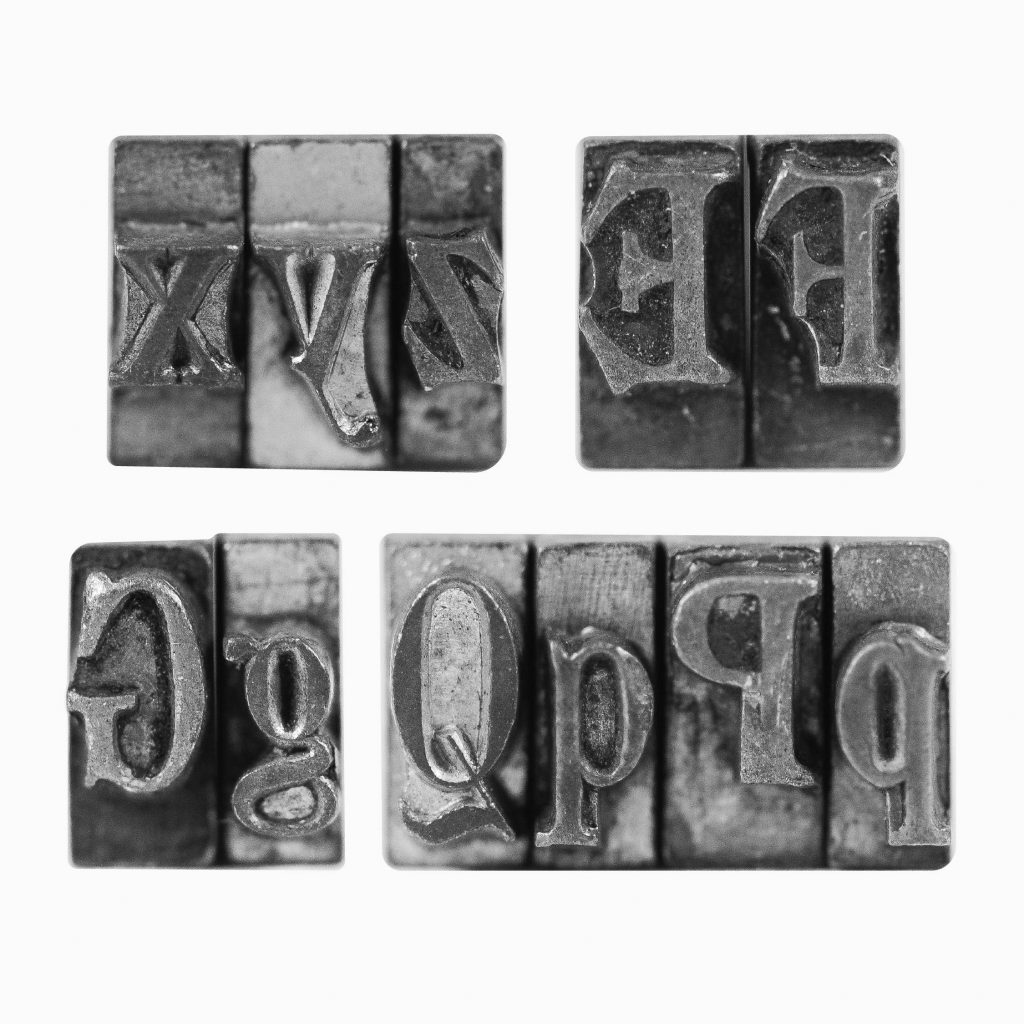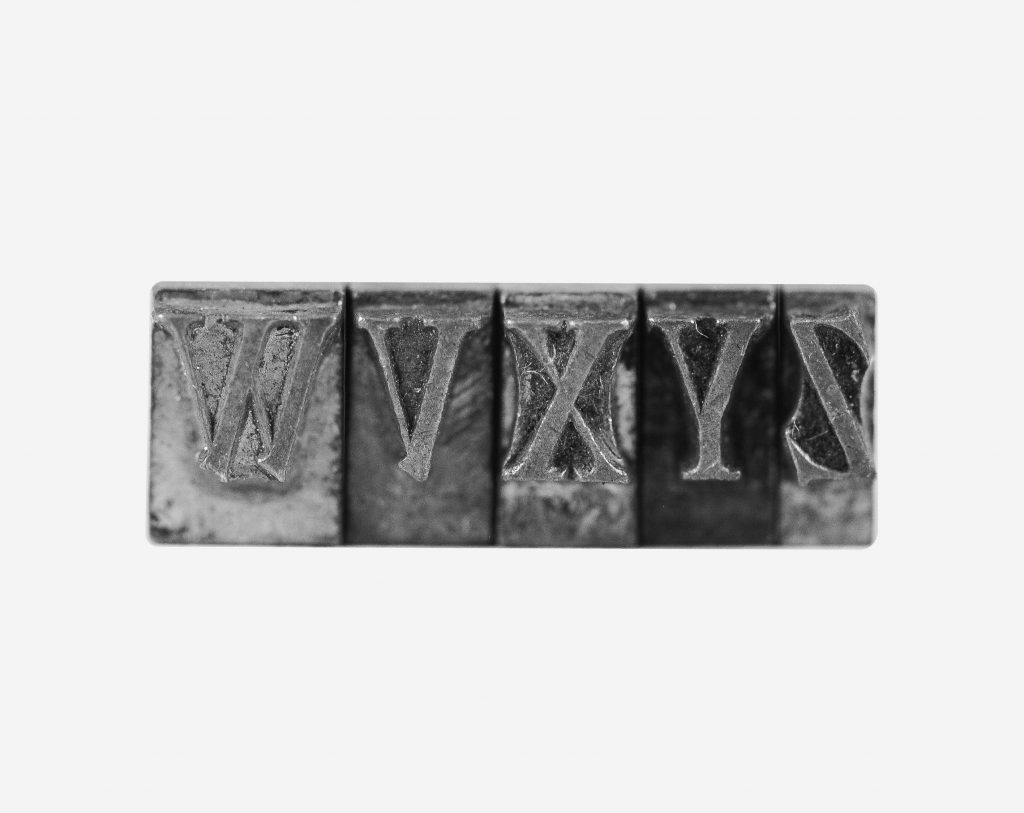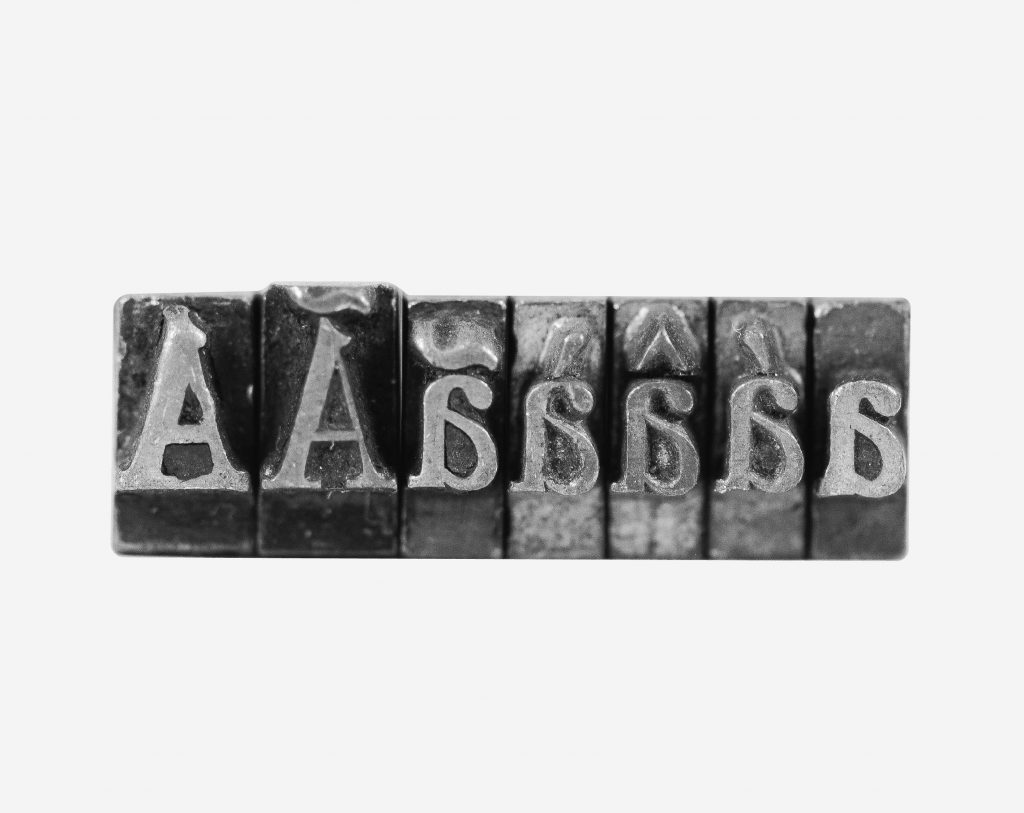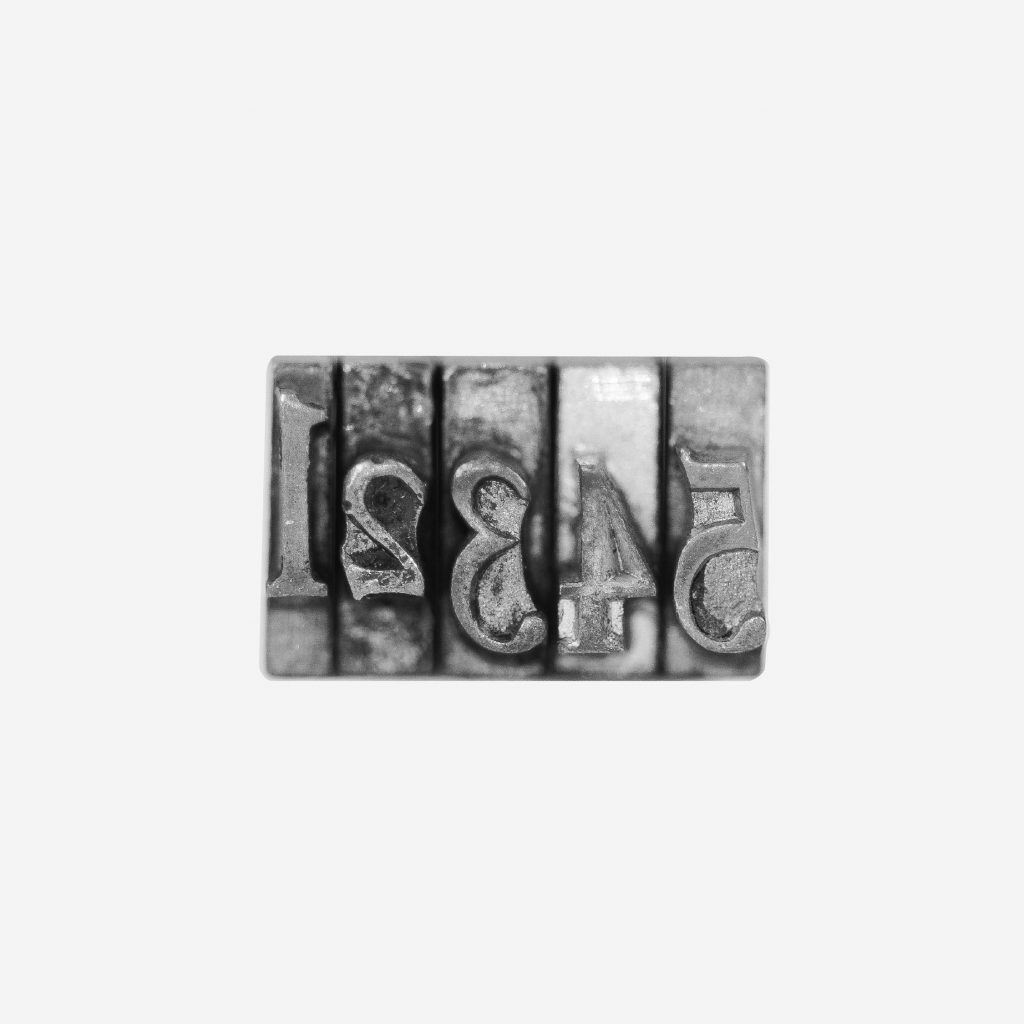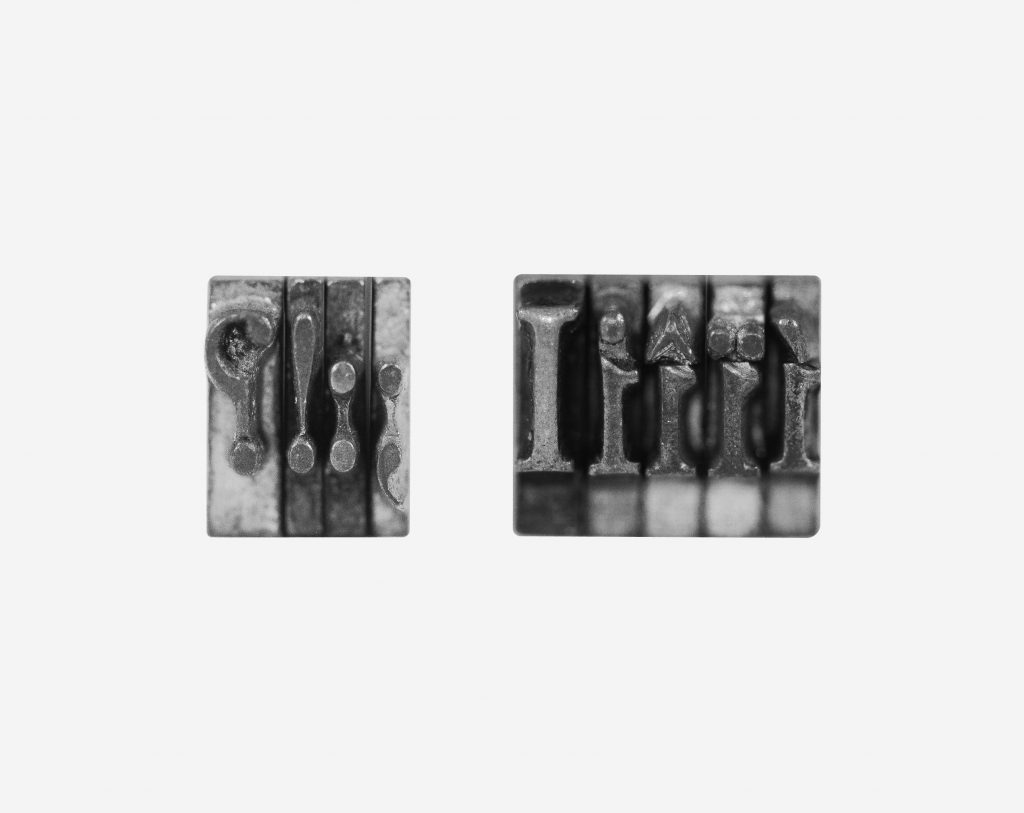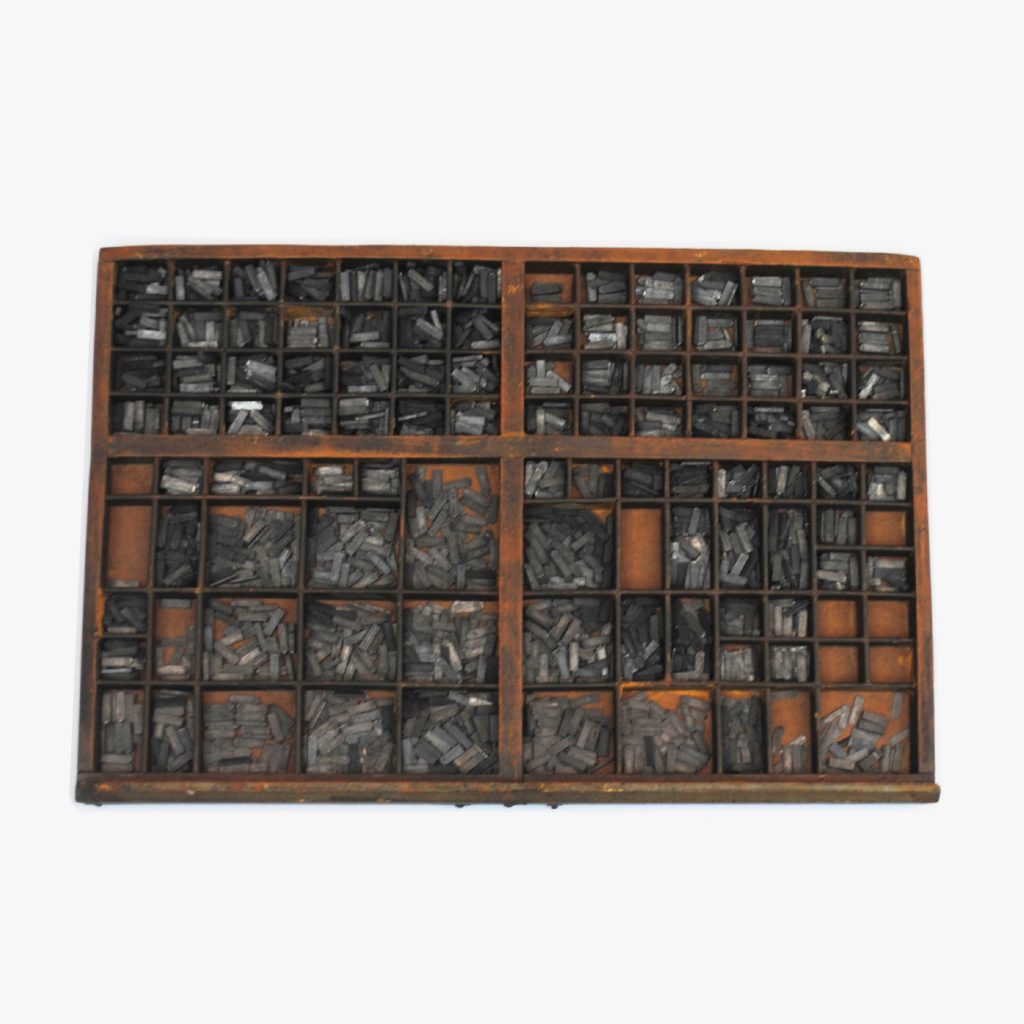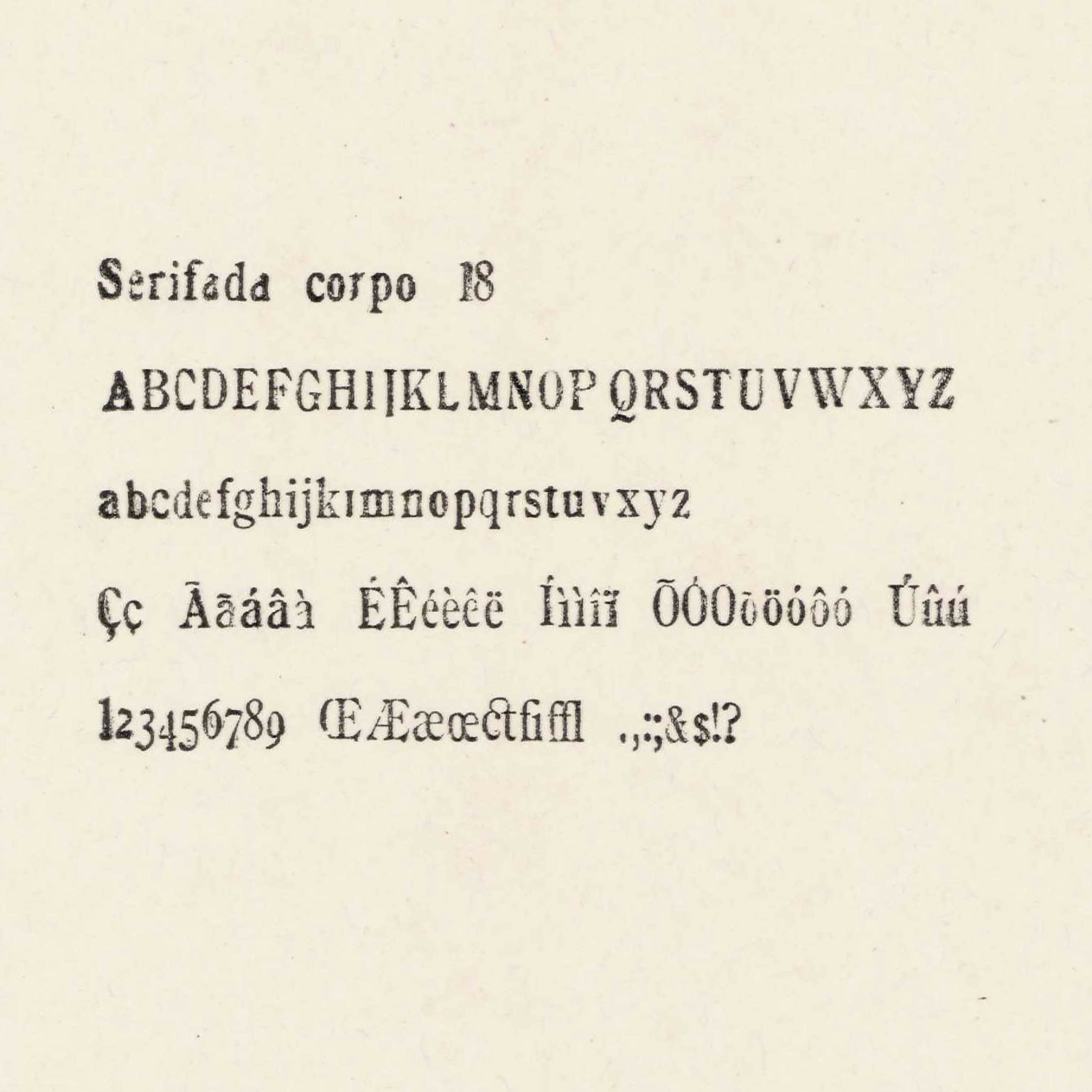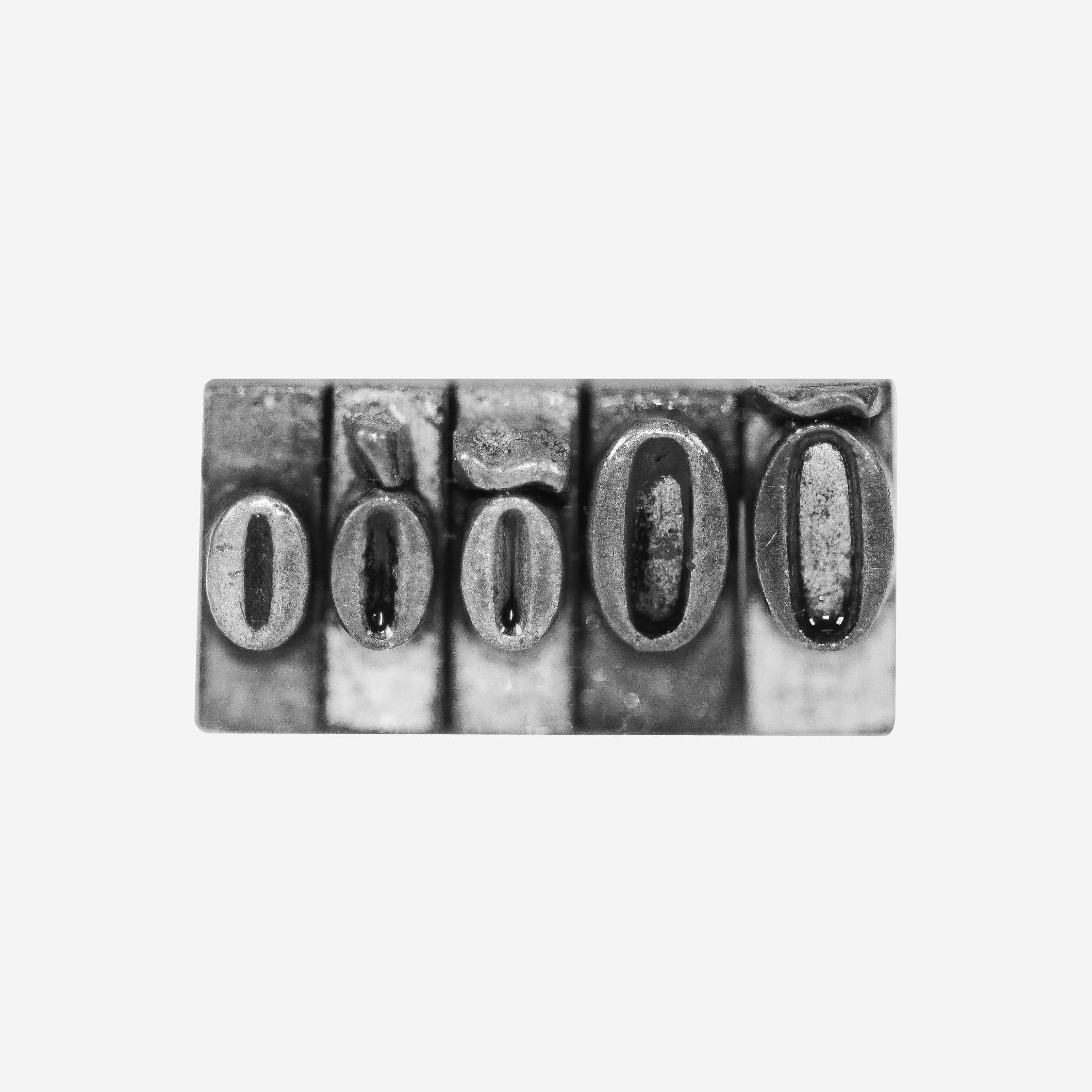
[Rinascimento Nero] character set -
[Rinascimento Nero] consoantes -
[Rinascimento Nero] wvxyz -
[Rinascimento Nero] A -
[Rinascimento Nero] o -
[Rinascimento Nero] numerais -
[Rinascimento Nero] ae -
[Rinascimento Nero] i pontuacoes -
[Rinascimento Nero] gaveta
[Rinascimento Nero] 18pt
Estilo
Serifada
Corpo (pt)
18
Caracteres Chave
C, Q, a, g
Fundidora
[Nebiolo]
Catálogo
Nebiolo [ca. 1900]
Tipo de Inscrição
Rasgo quadrado
Localização da Inscrição
Base do tipo
Estado de Conservação
Marcas de uso recorrente; alguns tipos apresentam desgaste na face que pode comprometer a qualidade da impressão.
História do Estilo
Semelhante à família Rinascimento Nero (Nebiolo, [ca. 1900]), essa fonte possui um nome comum que não permitiu com que fossem encontradas mais informações a respeito de seus desenhos originais e fundidora de origem. Após a comparação digital, foi confirmada essa semelhança com a Rinascimento Nero em todos os aspectos analisados.